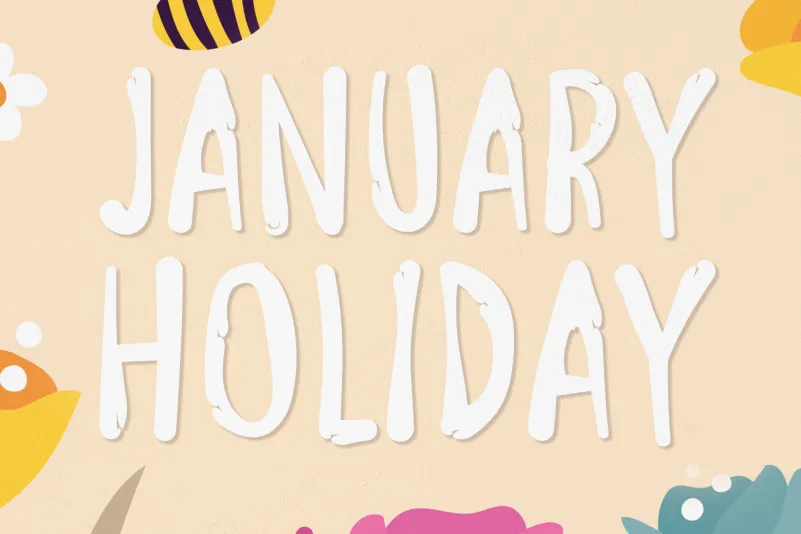
January Holiday Display Font – Download Grátis
A fonte ‘January Holiday Display Font’ é perfeita para quem busca uma maneira única de ilustrar suas ideias criativas durante as férias de inverno. Desenhada pelo artista aprimorado andikastudio, esta escolha se destaca com linhas bold e estreitas, projetadas para destacar os seus conceitos mais audaciosos. Seja em um projeto de design gráfico, em uma apresentação ou até mesmo em um relatório de trabalho, adicionar esta fonte pode transformar a forma como suas ideias são expressas. É ideal para quando você quer fazer com que as pessoas percebam, apreciem e se lembrem da sua visão. Adicione ‘January Holiday Display Font’ ao seu próximo projeto visual e deixe-se impressionar pela maneira como ela renova e ilumina seus ideais mais inusitados. Tudo isso em uma fonte que combina facilmente com o tema festivo do mês de janeiro, tornando-a perfeita para projetos natalinos ou mesmo para apresentações escolares que têm a data corrente como base.